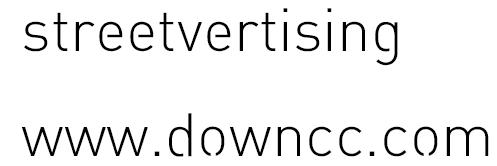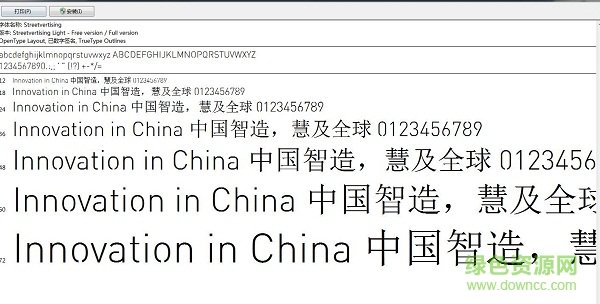
streetvertising字體是一款線條纖細(xì)的無(wú)襯線字體,字形刻畫(huà)細(xì)膩,識(shí)別性高,給人非常現(xiàn)代、年輕的感覺(jué),有需要者歡迎在綠色資源網(wǎng)免費(fèi)下載!
1.適用于標(biāo)題、廣告,瞬間的識(shí)別性高
2.筆畫(huà)粗細(xì)對(duì)比小,視覺(jué)上看起來(lái)基本一致
3.完全拋棄裝飾襯線,只剩下主干,造型簡(jiǎn)明有力,更具現(xiàn)代感